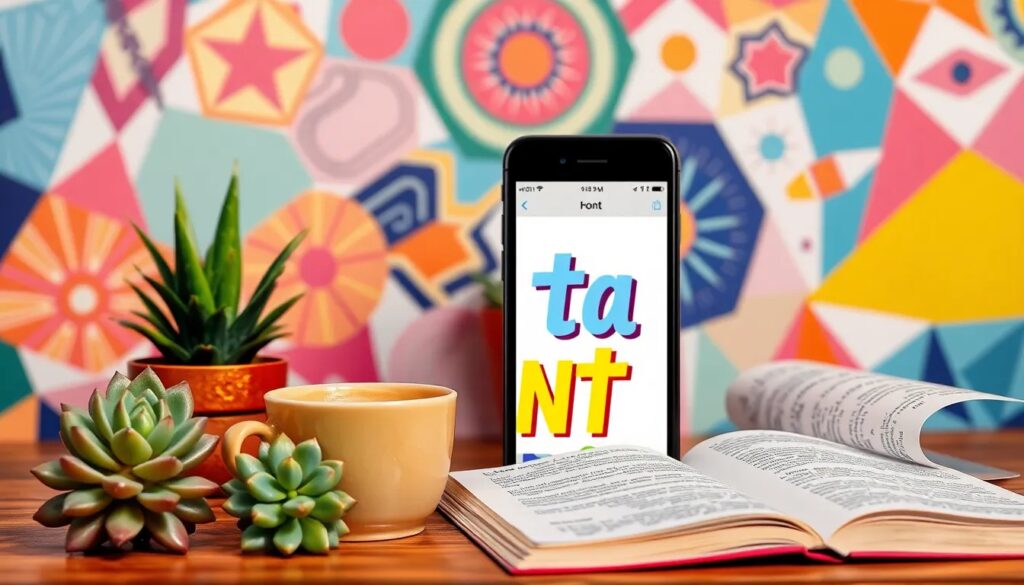
Font para Instagram: generador de letras especiales
En la actualidad, las redes sociales han revolucionado la forma en que nos comunicamos y expresamos nuestras ideas. En este contexto, el uso de fuentes personalizadas se ha vuelto esencial para destacar entre la multitud. En este artículo, exploraremos cómo utilizar un font para Instagram, una herramienta útil para crear textos únicos y atractivos para tus publicaciones.
Con el auge de Instagram, los usuarios buscan constantemente maneras de hacer que sus perfiles sean más llamativos. Una de las mejores maneras de lograrlo es mediante el uso de un generador de letras que permite cambiar la tipografía de manera rápida y sencilla.
Cómo funciona el generador de letras para Instagram
El generador de letras para Instagram es una herramienta innovadora que permite a los usuarios crear textos con diferentes estilos tipográficos. Estos generadores utilizan caracteres Unicode, que son fácilmente copiados y pegados en varias plataformas sociales, como Instagram, Facebook y Twitter.
Los usuarios pueden elegir entre una amplia variedad de estilos, como:
- Contorno
- Versalitas
- Burbujas
- Negrita
- Cursivas
- Texto invertido
Además, estos generadores permiten combinar letras con emojis o símbolos, lo que añade un toque creativo a las publicaciones. La herramienta es intuitiva, lo que significa que no se requieren habilidades técnicas para usarla.
Qué son las letras para Instagram y para qué sirven
Las letras para Instagram son variaciones de texto que se pueden usar en publicaciones, comentarios y biografías. Su propósito es personalizar y embellecer el contenido, haciéndolo más atractivo para los seguidores. Utilizar diferentes estilos de texto puede ayudar a destacar información clave o hacer que una publicación sea más interesante.
Entre sus principales usos, encontramos:
- Mejorar la estética de la biografía de Instagram.
- Resaltar mensajes importantes en publicaciones.
- Agregar un toque personal a los comentarios.
Al utilizar letras personalizadas, puedes crear una identidad visual coherente que atraiga a más seguidores y genere interacciones.
Cómo generar fuentes de Instagram para copiar y pegar
Generar fuentes para Instagram es un proceso sencillo. Primero, debes acceder a un generador de letras en línea, donde podrás introducir el texto que deseas estilizar. Una vez que hayas escrito tu mensaje, el generador te mostrará diferentes opciones de fuentes.
Para copiar las letras generadas, simplemente selecciona el estilo que más te guste y haz clic en el botón de copiar. Después, solo debes pegar el texto en Instagram en el lugar deseado.
Consejos para un uso efectivo:
- Prueba diferentes estilos para ver cuál se adapta mejor a tu contenido.
- Combina letras con emojis para un mayor impacto visual.
- Evita usar demasiados estilos en una misma publicación para no crear confusión.
Cuáles son los tipos de letras más usadas en Instagram
En Instagram, hay una gran variedad de tipografías populares que los usuarios utilizan para destacar sus publicaciones. Algunas de las más comunes incluyen:
- Negrita: Para resaltar información clave.
- Cursivas: Para dar un toque elegante.
- Versalitas: Para títulos o frases llamativas.
- Texto invertido: Para un efecto visual sorprendente.
Aparte de estas, el estilo de burbujas y otros diseños creativos se han vuelto populares para dar un aspecto divertido a las publicaciones. Instagram se caracteriza por su estética visual, y usar diferentes tipos de letras puede ser una excelente forma de captar la atención de tus seguidores.
Cómo usar el generador de letras para Instagram
Usar un generador de letras para Instagram es bastante fácil y no requiere habilidades técnicas. A continuación, te explicamos los pasos básicos:
- Visita un sitio web que ofrezca un generador de letras.
- Escribe el texto que deseas modificar.
- Explora las diferentes opciones de fuentes disponibles.
- Selecciona la fuente que más te guste y cópiala.
- Pega el texto en tu publicación o biografía de Instagram.
Esta herramienta no solo es fácil de usar, sino que también permite a los usuarios experimentar con diferentes estilos para encontrar el que mejor se adapte a su personalidad.
Dónde encontrar letras bonitas para copiar y pegar en Instagram
Existen varias plataformas donde puedes encontrar letras bonitas para Instagram. Algunas de las más populares incluyen:
- Glyphy: Ofrece más de 299 estilos de texto y emoticones.
- Sitios de generadores de fuentes en línea que permiten seleccionar y personalizar textos.
- Aplicaciones móviles que permiten crear y guardar tus fuentes favoritas.
Por último, recuerda que al utilizar un font para Instagram, estás mejorando la visibilidad de tu contenido. Personalizar tus publicaciones no solo las hace más atractivas, sino que también puede aumentar la interacción de tus seguidores.